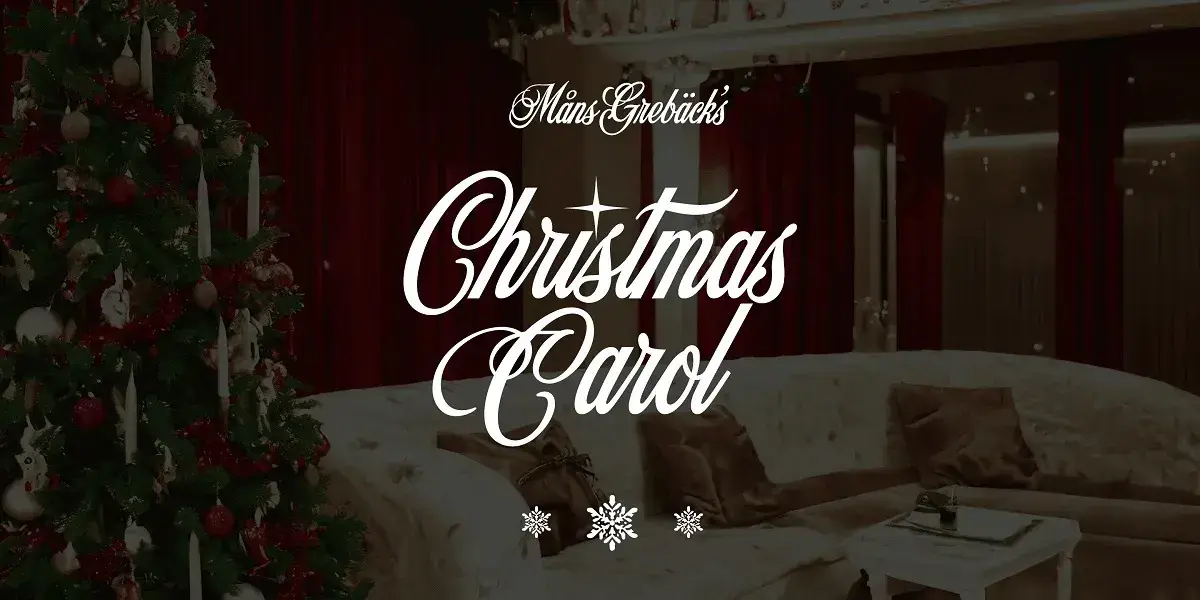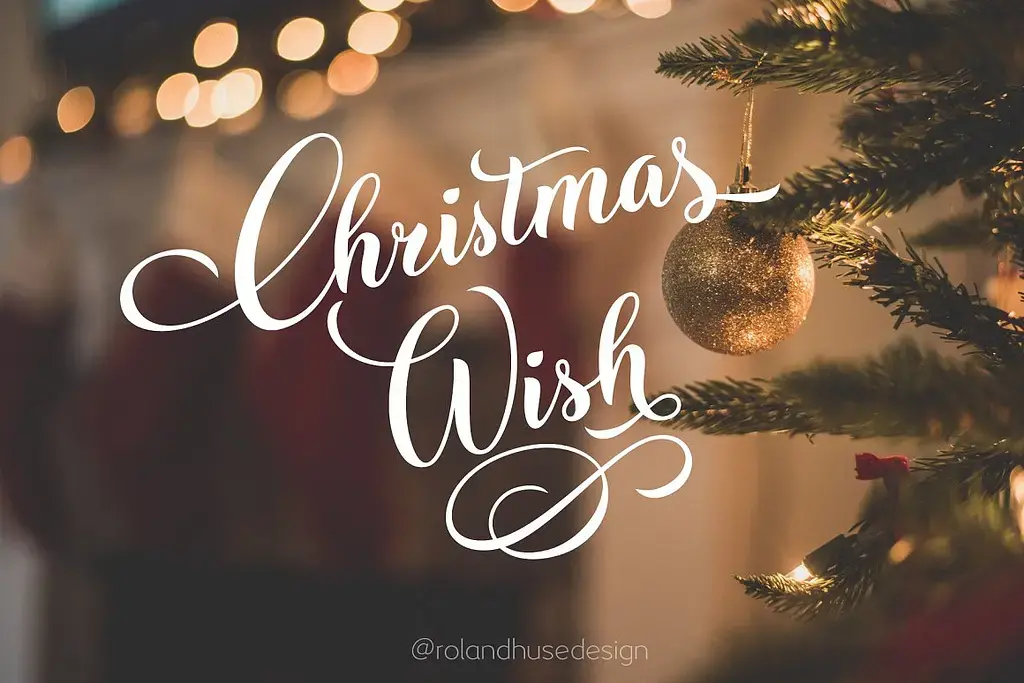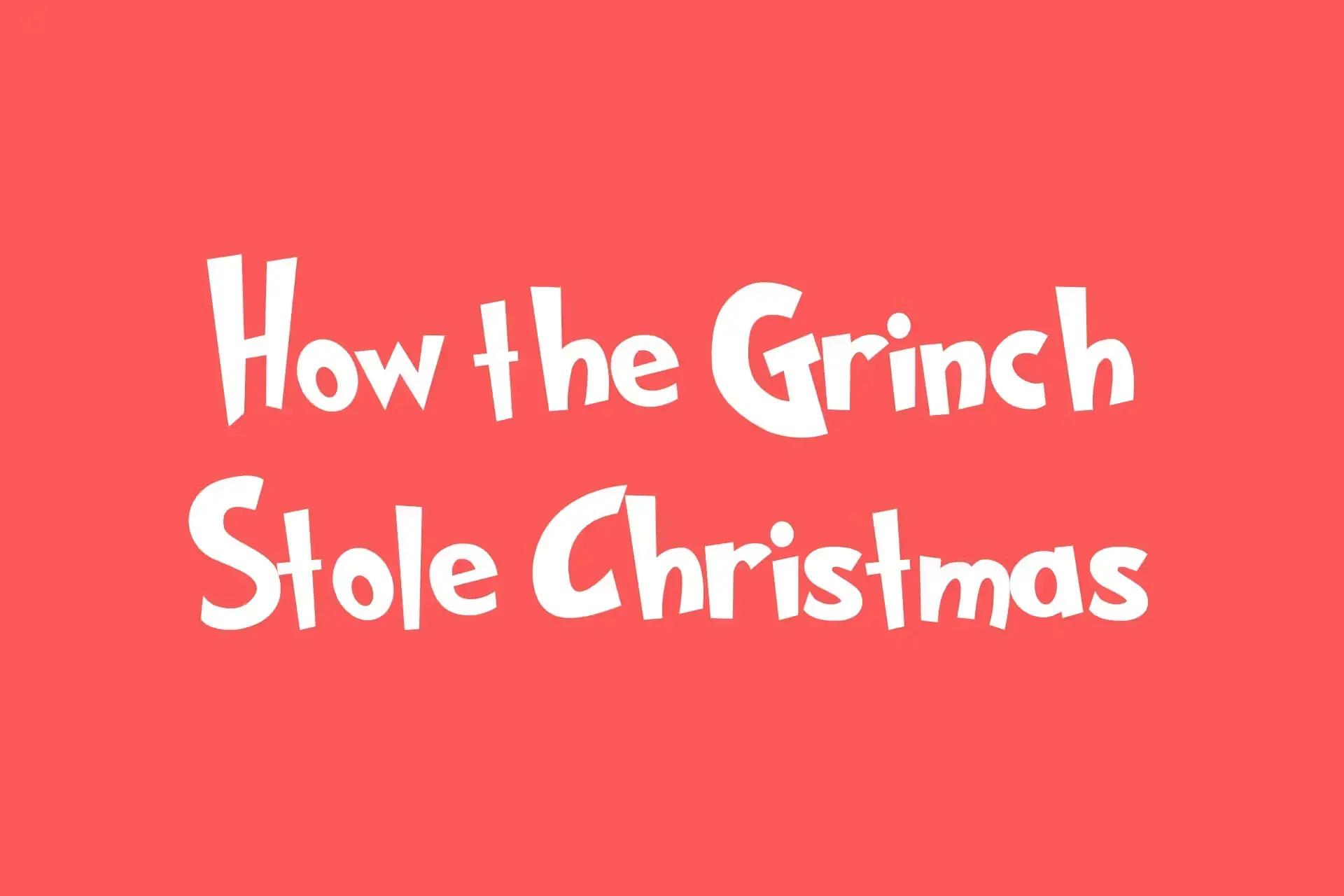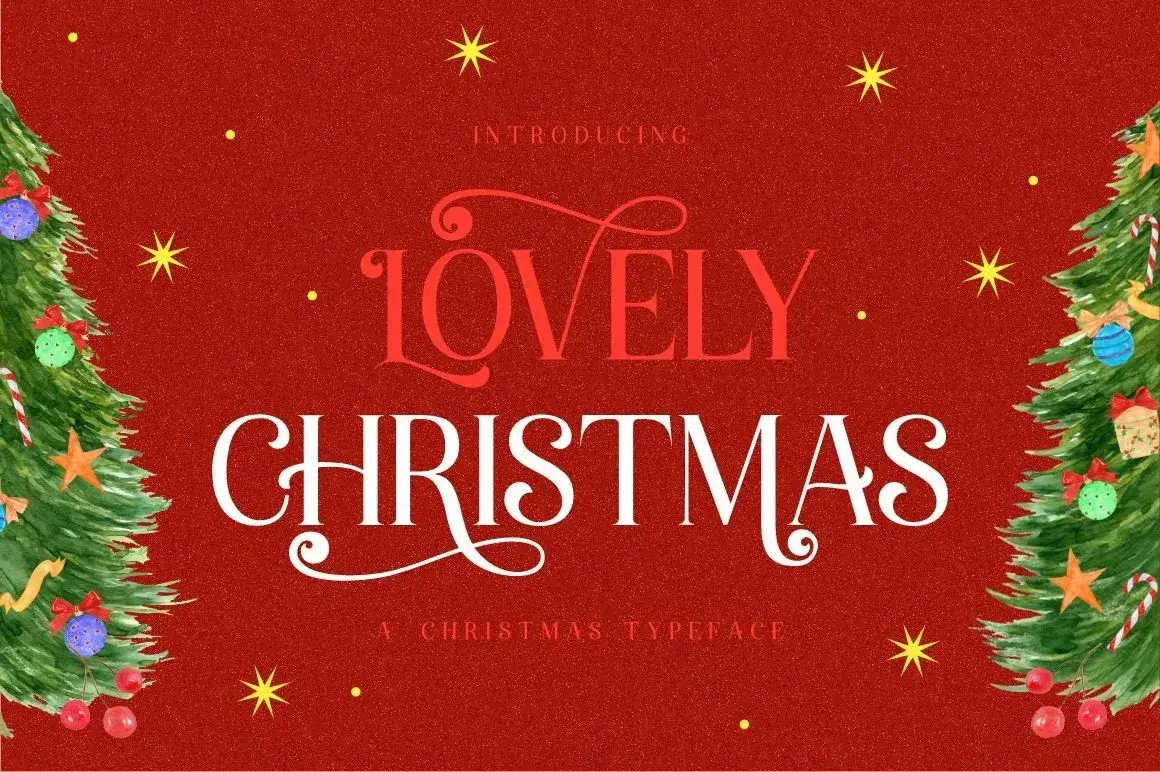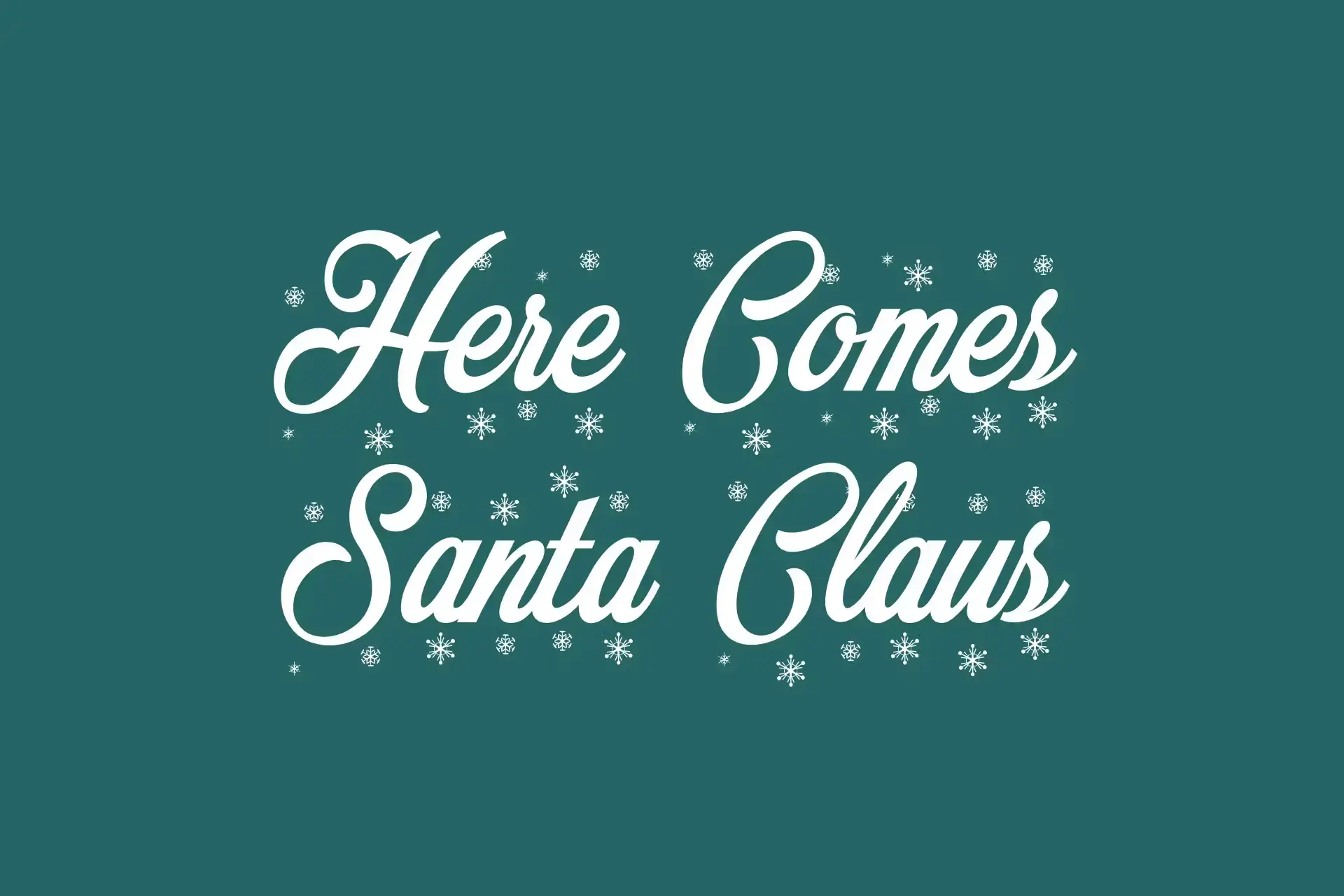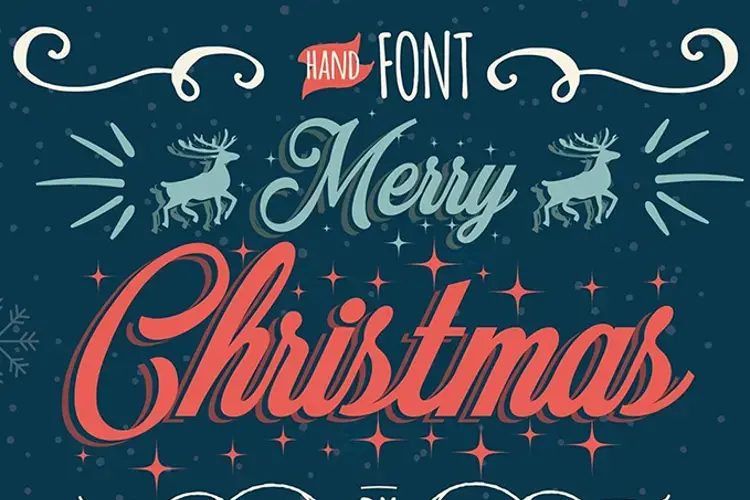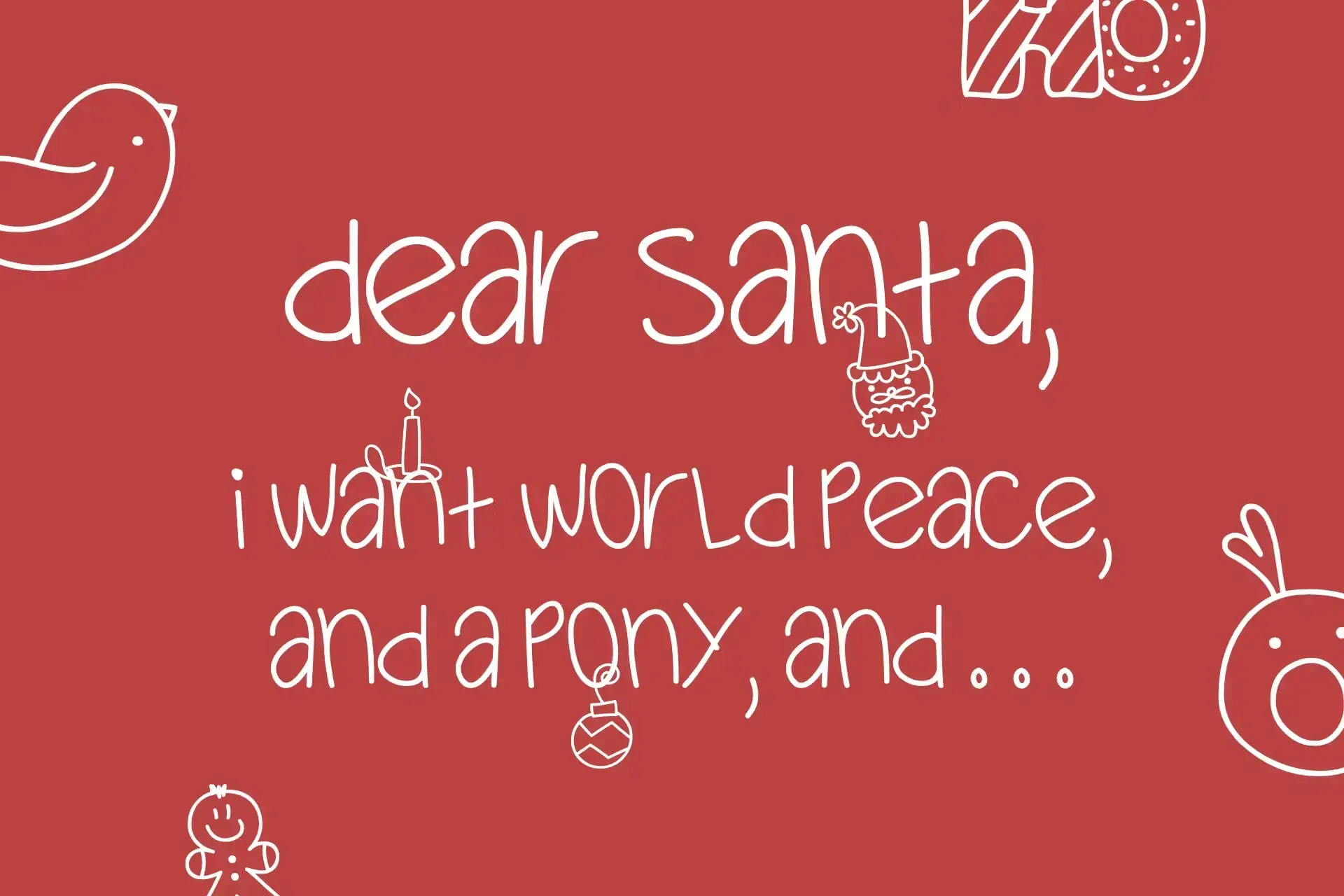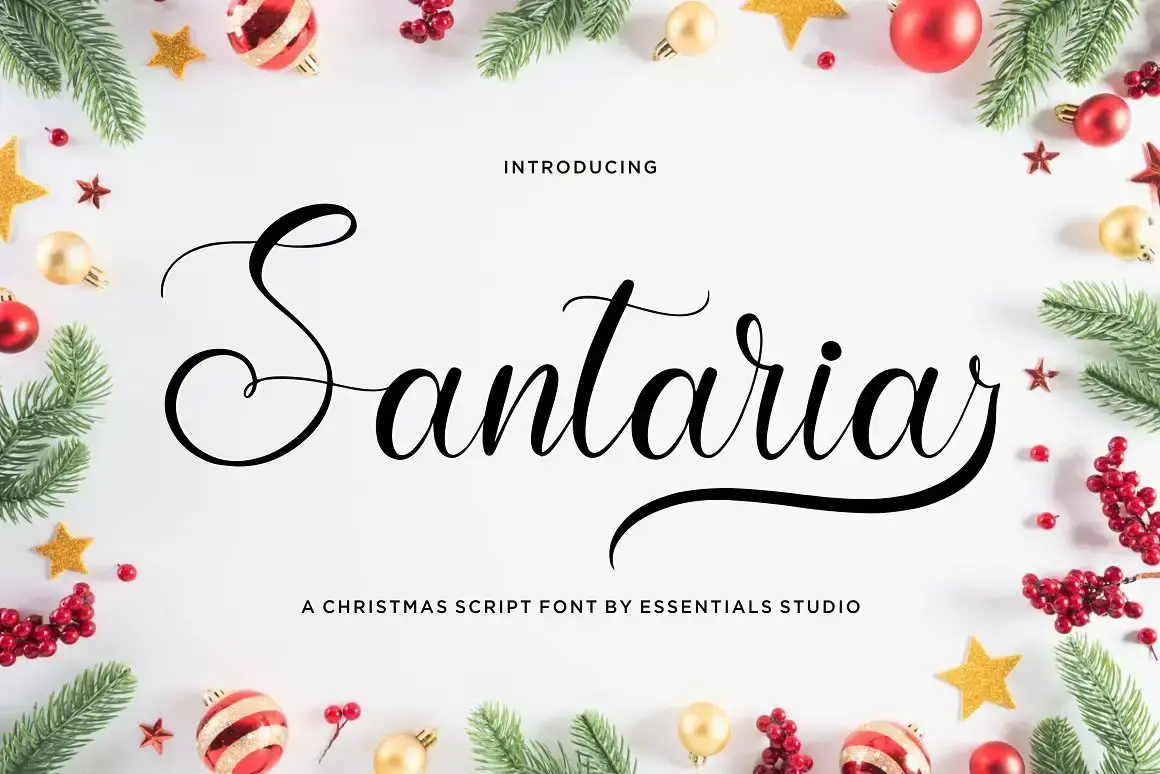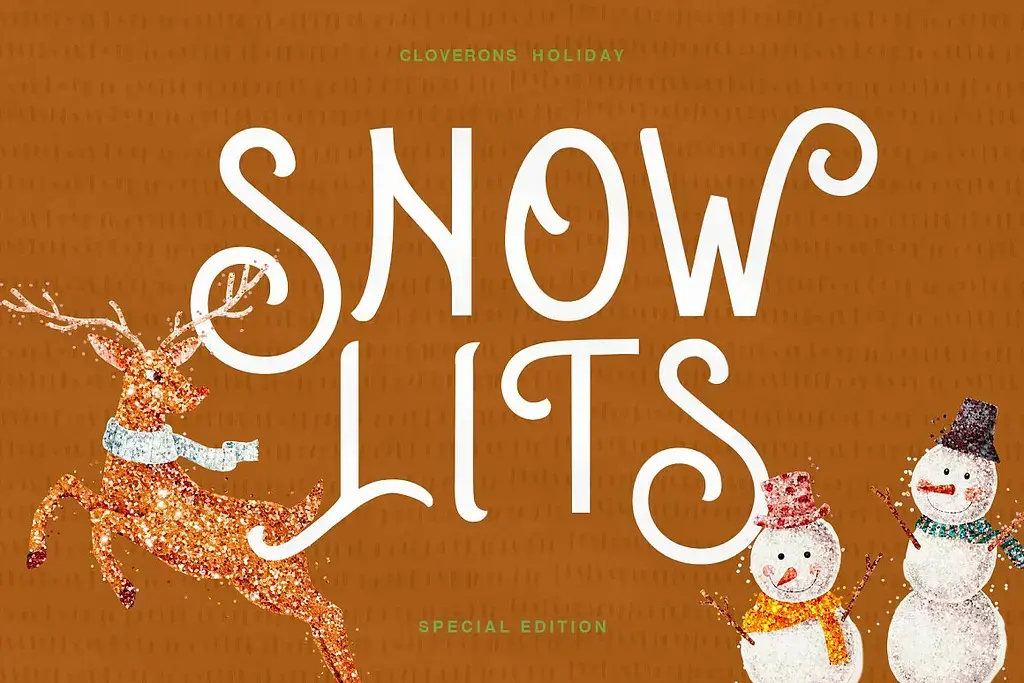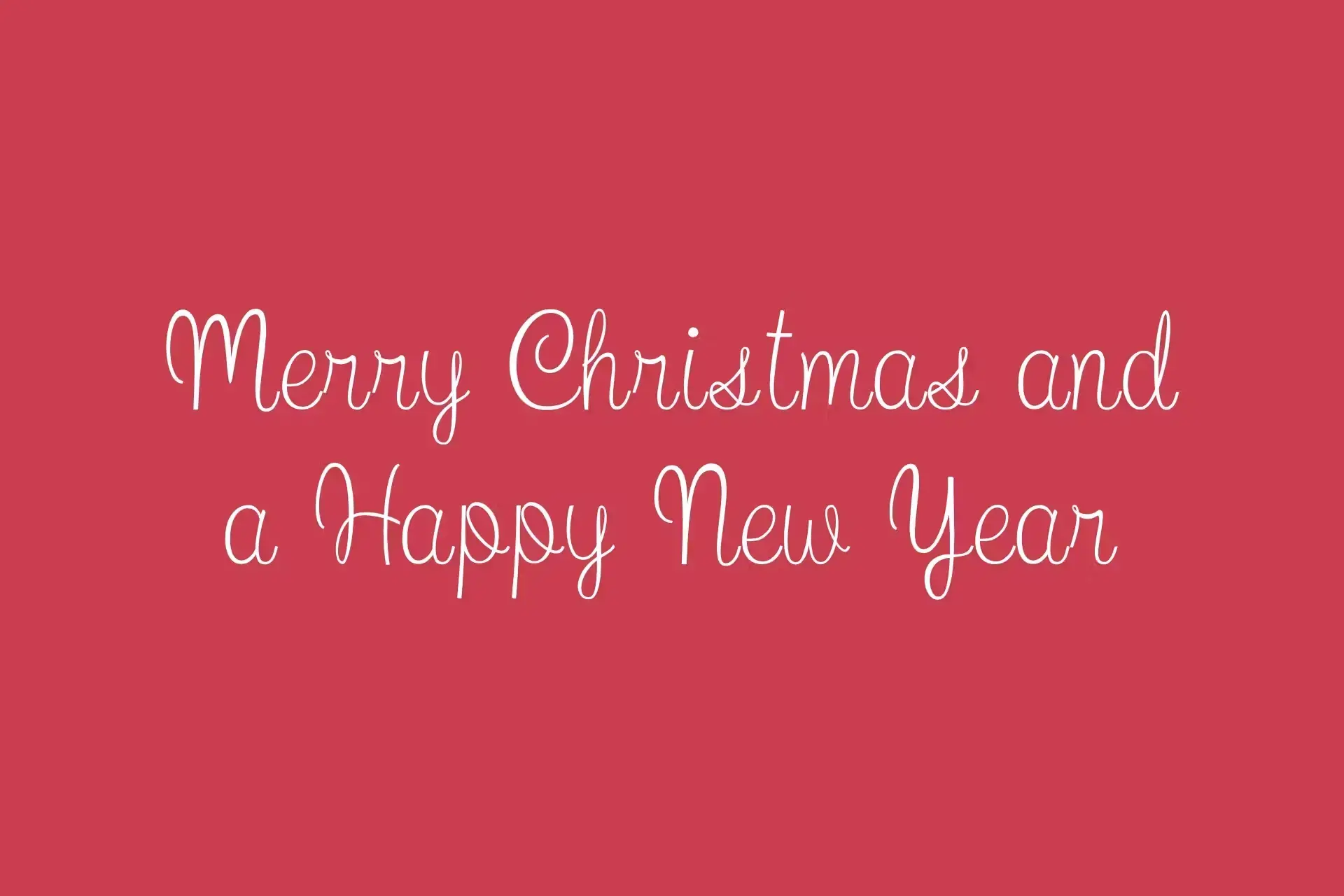
Top 10 des polices d'écriture de Noël gratuites à télécharger
Plongez dans un monde où les lettres dansent au rythme des festivités avec notre sélection exclusive des meilleures polices d'écriture de Noël. Les Christmas fonts que nous avons rassemblées capturent l'esprit des fêtes, ajoutant une touche enchantée à chaque mot et chaque design.
Des typographies de Noël élégantes aux styles ludiques, notre top 10 de polices d'écriture de Noël offre un éventail de choix pour transformer vos créations en véritables chefs-d'œuvre festifs. Que vous soyez à la recherche de calligraphies étincelantes ou de caractères chaleureux, ces polices de Noël gratuites à télécharger ajouteront une dose d'émerveillement à vos projets graphiques.